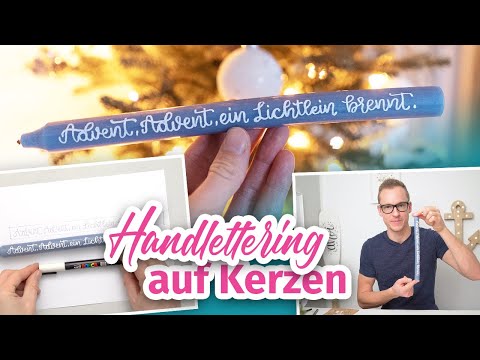
Kerzen zu beschriften ist (mal wieder) eine ganz neue Herausforderung – egal ob du bereits sicher im Handlettering bist, oder nicht.
Vor einiger Zeit habe ich einige Kerzen im Internet entdeckt, die wirklich wunderschön beschriftet waren. Und glücklicherweise hat sich die talentierte Künstlerin hinter den Kerzen bereit erklärt, ein kleines Tutorial für den Blog zu schreiben.
Kerzen beschriften Schritt für Schritt
Bevor du loslegst, solltest du dir überlegen, welchen Spruch bzw. welches Wort du auf die Kerze bringen möchtest, damit du dann die Größe der Kerze festlegen kannst.
Natürlich geht es auch umgekehrt, du passt den Spruch an die Größe der vorhandenen Kerze an.
Benötigtes Material
- Kerze (weiß)
- Papier
- Bleistift/Schere
- Seidenpapier (weiß)
- Brushpen (Fudenosuke hart oder Pentel Sign Touch) oder Fineliner
- Backpapier
- Heißluftföhn (oder einen normalen Föhn)
Schritt 1: Das Lettering
Lettere deinen Spruch mit dem Brushpen (oder monoline mit einem Fineliner) auf ein Blatt Papier und halte dich dabei platzmäßig an die Größe der Kerze.
Du kannst den Spruch gerne mit Bleistift vorschreiben.
Tipp: Mit dem Handlettering-Generator kannst du ein komplettes Layout planen oder sogar eine Vorlage zum Ausdrucken kreieren.
Schritt 2: Abpausen
Pause nun den Text – ebenfalls mit dem Brushpen – auf ein Stück Seidenpapier.
Beachte dabei, dass du die glatte, etwas glänzende Seite des Seidenpapiers beschriftest und sei vorsichtig beim Schreiben, damit das Papier nicht reißt.
Geübte können Schritt 1 auch auslassen und direkt auf das Seidenpapier lettern.
Schritt 3: Ausschneiden
Schneide jetzt den Spruch aus und schau, dass du so knapp wie möglich an der Schrift bleibst.
Der Rand rund um den Text sollte also so gering wie möglich gehalten werden.
Schritt 4: Position finden
Platziere nun den zugeschnittenen Text mit der glatten, also beschrifteten Seite nach oben auf der Kerze (heißt, du kannst den Text lesen, wenn du auf die Kerze schaust).
Schritt 5: Platzierung festhalten
Lege ein Backpapier über den Text. Es sollte nur so groß sein, dass die Kerze abgedeckt ist und du es hinten auf der Rückseite der Kerze noch gut fassen kannst.
Eine Metallklammer ist dabei recht hilfreich, gerade bei kleineren Kerzen, da es beim nachfolgenden Föhnen recht heiß werden kann.
Pass dabei auf, dass das Seidenpapier darunter keine Falten wirft oder „Eselsohren“ bekommt.
Schritt 6: Handlettering fixieren
Nun föhne ganz vorsichtig über das Backpapier. Dabei solltest du nicht zu lange auf einer Stelle bleiben und am besten den Föhn dauernd in Bewegung halten.
Sobald sich das Seidenpapier mit dem warmen Wachs verbindet, wird die Stelle dunkler. Du kannst auch zwischendurch immer mal ganz vorsichtig unter das Backpapier schauen, wenn du dir nicht sicher bist, ob schon alles miteinander verschmolzen ist.
Grundsätzlich ist es reine Übungssache und je öfter du es machst, umso mehr Fingerspitzengefühl bekommst du.
Ich streiche auch beim Föhnen hin und wieder mal vorsichtig mit der flachen Hand übers Backpapier, um eventuelle Unebenheiten darunter zu glätten.
Schritt 7: Deine Kerze bewundern
Wenn der gesamte Text dunkel ist, was bedeutet, dass sich das komplette Seidenpapier mit der Kerze verbunden hat, lässt du das Ganze etwas abkühlen.
Anschließend kannst dann das Backpapier langsam abziehen.
Et voilà ! … FERTIG!
Tipps zur Umsetzung
Du kannst deinen Text natürlich auch mit farbigen Brushpens (Fudenosukes oder Pentel Touch Sign Pens gibt es auch farbig) schreiben oder mit anderen, dickeren Brushpens Farbakzente setzen, wie z.B ein Herz als Untergrund für den Text malen.
Das Seidenpapier wird dann allerdings etwas wellig, was sich auch beim Endergebnis bemerkbar macht.
Aber es ist Handarbeit und ich finde, das darf man auch sehen.
So, nun wünsche ich dir viel Spaß beim Gestalten deiner Kerzen. Gelegenheiten, sie zu verschenken (Ostern, Muttertag …) kommen ja nun einige auf uns zu und in Zeiten wie diesen, freut sich bestimmt auch so mancher über ein Paket mit individuellen Kerzen.
Eigentlich über die klassische Kalligrafie. Ich habe aber immer schon gerne geschrieben und Karten gestaltet und schon damals, als es noch keine Begriffe, wie Faux Calligraphy und Brushlettering gab, habe ich versucht, dieses schöne Schriftbild der Federkalligrafie mit Stiften und doppelten „Abstrichen“ zu imitieren.